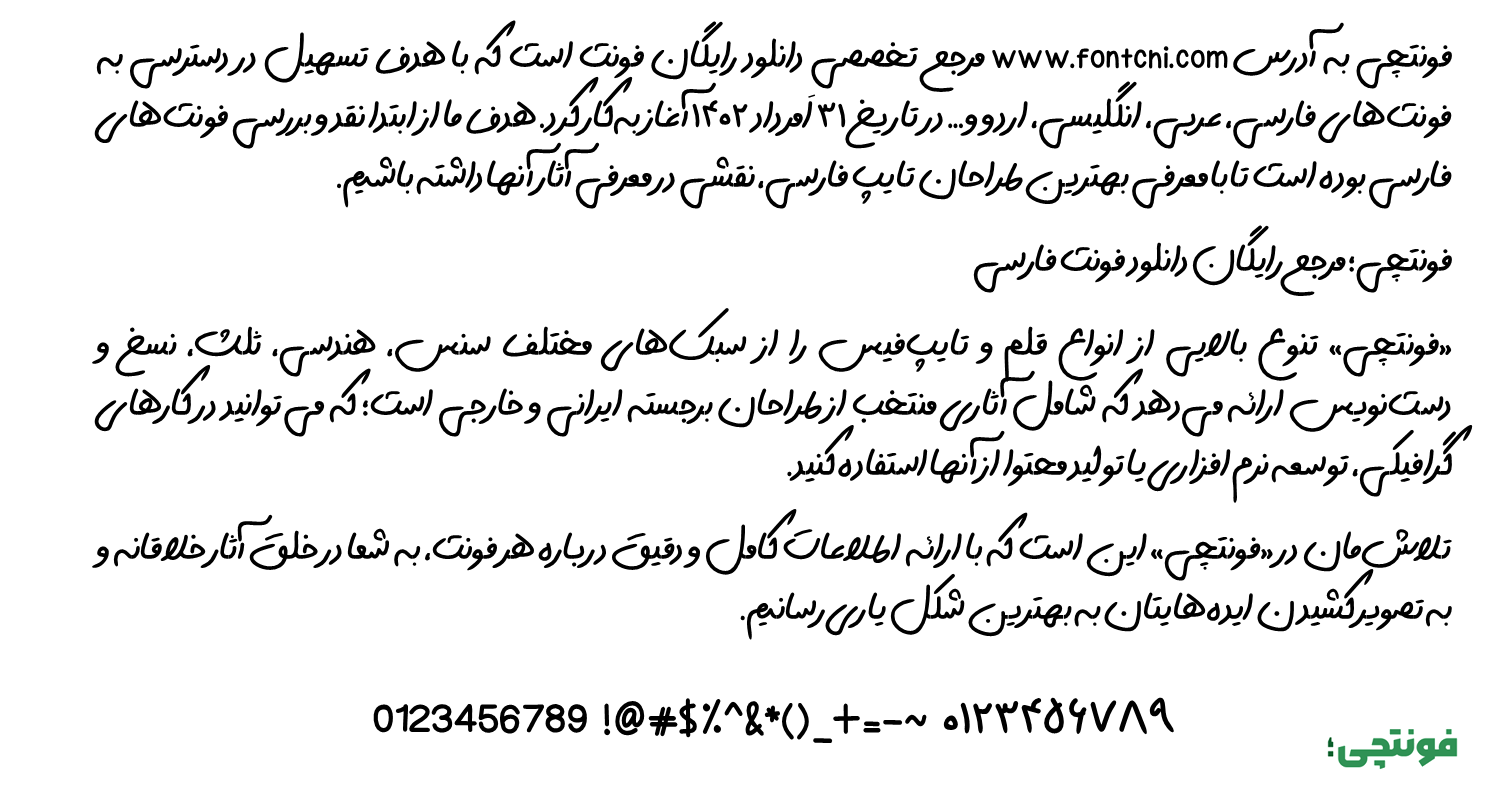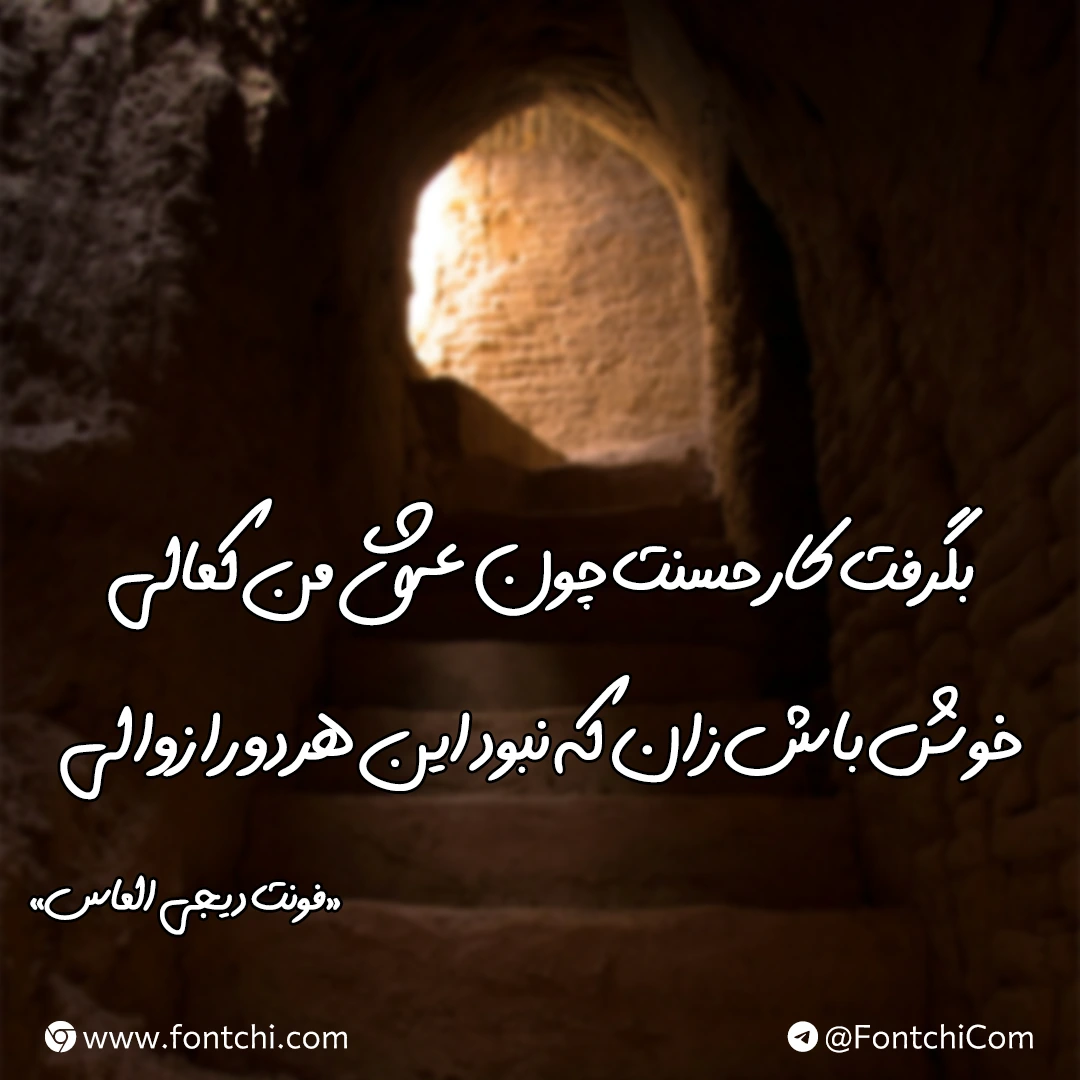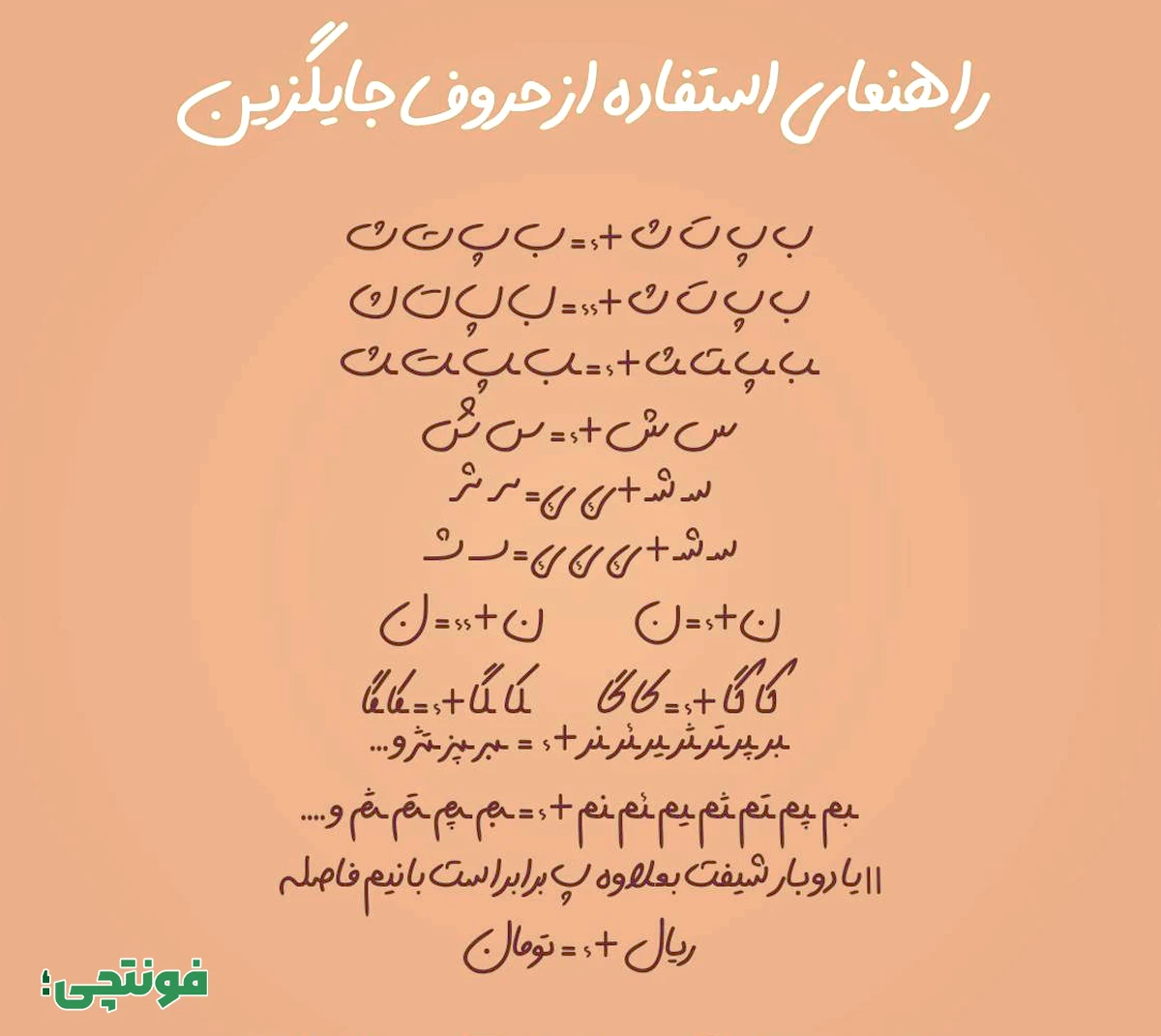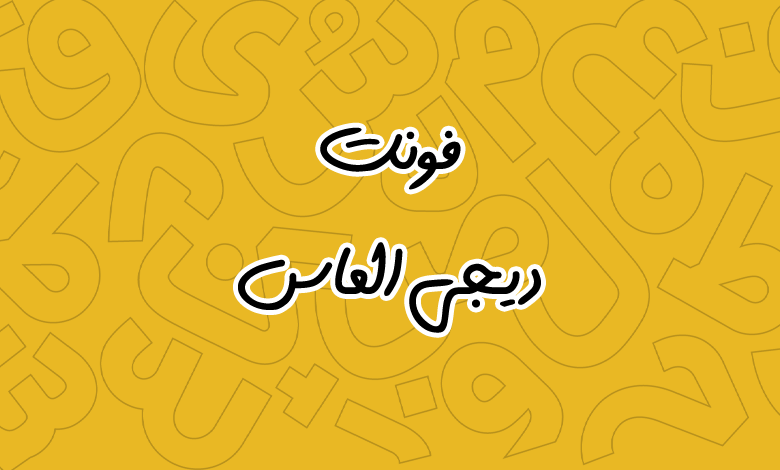
فونت دیجی الماس (Digi Almas)
فونت دیجی الماس یا فونت الماس (به انگلیسی: Digi Almas) از سری فونت دستنویس فارسی است که با پشتیبانی از حروف جایگزین و زبانهای مختلف برای استفاده در کارهای گرافیکی و نمایشی مورد توجه قرار گرفته است. این فونت بولد با ظاهر پر انرژی و نسبتا درشتی که دارد، اما در اندازههای بزرگ آنطور که باید بولد نیست و بیشتر به وزن معمولی شباهت دارد.
فونت الماس توسط مهدی برقگیر بر اساس دستخط طیبه مرادی طراحی شده است که دارای شخصیتی ساده، روان و در عین حال عاشقانه و جذاب است که برای استفاده در عناوین و کارهای خاص کاربرد دارد. در ادامه به بررسی کامل این فونت جدید فارسی میپردازیم.
فونت دیجی الماس با استایل دستنویس و وزن بولد طراحی شده است که ظاهری روان، ساده و در عین حال پرانرژی به آن میبخشد. این وزن بولد باعث میشود فونت برای عناوین، پوسترها، استوریهای اینستاگرام و تایپوگرافیهای خلاقانه بسیار مناسب باشد.
این فونت فارسی از زبانهای دیگری همچون عربی، کردی و انگلیسی پشتیبانی میکند. پشتیبانی از سایر زبانها استانداردهای لازم را دارد. هم از نظر پشتیبانی اعراب و هم از نظر همنشینی گلیفهای تزئینی و نمایشی که موجب بههم ریختگی کلمات نمیشود. تنها کاستی فونت در بخش اعداد است که برای زبان فارسی و عربی اعداد «۴۵۶» بهصورت مختلط استفاده شده است.
از کاربردهای رایج این فونت میتوان به موارد زیر اشاره کرد:
- طراحی بنر، پوستر، جلد کتاب و عناوین.
- استفاده در شبکههای اجتماعی در استوری یا تامنیل پستها.
- استفاده بر روی محصولاتی همچون چاپ ماگ، تیشرت یا کارت پستالهای عاشقانه.
- مناسب برای کارهای تبلیغاتی که نیازمند ایجاد ارتباط صمیمی و نزدیک با مخاطب هستند.
حروف جایگزین فونت الماس دستنویس
یکی از ویژگیهای متمایز فونت الماس، وجود حروف و کلمات جایگزین (Alternate Glyphs) خودکار یا دستی (اختیاری) است که به افزایش خوانایی و زیبایی بصری متن کمک میکند. این قابلیت به طراحان اجازه میدهد تا با خلاقیت بیشتری طرحهای منحصربهفرد خلق کنند.
این ظاهر متفاوت در شبکههای اجتماعی یا کاربردهای تبلیغاتی تاثیر بیشتری روی نگاه مخاطب میگذارد که موجب افزایش نرخ کلیک و نمایش خواهد شد.
همانطور که در تصویر بالا میبینید این امکان را در اختیار دارید که برای حروف و ترکیبات بالا چند نوع نوشتار مختلف را داشته باشید. این ویژگی اجازه میدهد بدون نیاز به انجام کارهای زمانبر در فتوشاپ یا نرمافزارهای نگارش متن، حروف را با ظاهری متفاوت تایپ کنید.